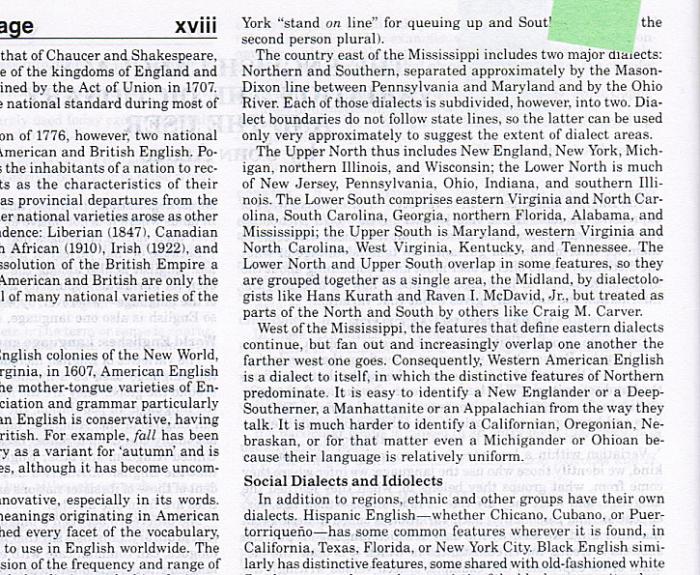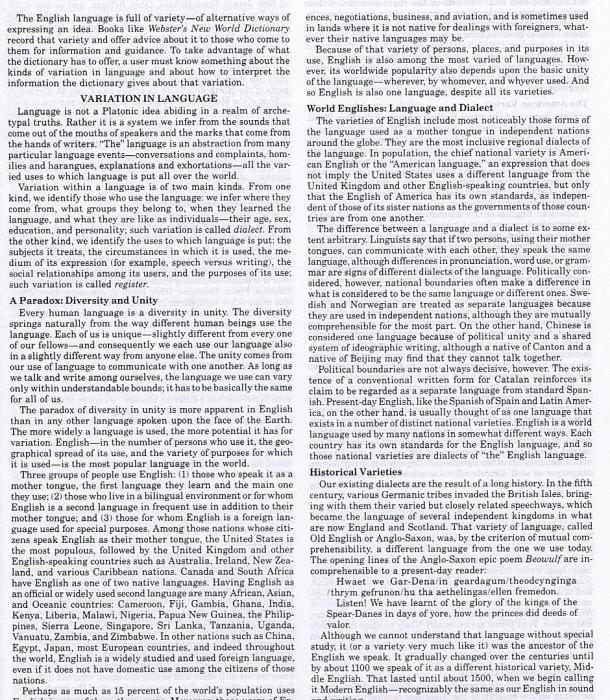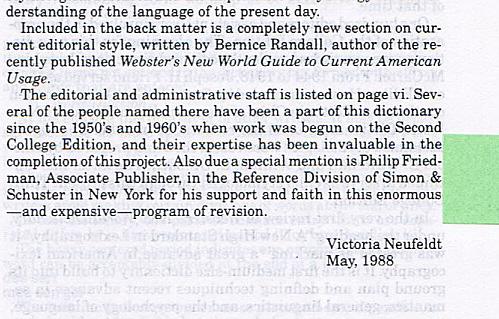
Der Bis-Strich im Englischen – wie wird der gehandhabt?
8th–9th November 2013
oder
8th – 9th November 2013
oder ganz anders?
Der — darf nicht verwendet werden ;-)
Aus (geisteswissenschaftlichen) Publikationen englischer und amerikanischer Verlage kenne ich nur den Halbgeviertstrich ganz ohne Leerraum; da handelt es sich allerdings nicht um Datumsangaben.
Ich kann mich an zwei Tagungsplakate erinnern, wo das Datum wie in Deinen Beispielen auftauchte – dort jeweils mit schmalem Leerraum davor und danach (bzw. im einen Fall, wo "th" hochgestellt war, nur mit zusätzlichem schmalem Leerraum danach, um die Abstände vor und nach dem Bis-Strich harmonisch zu gestalten). Also: kein ganzes Leerzeichen, aber ein bisschen Luft, damit der Bis-Strich nicht an den Zahlen klebt.
mathew butterick schreibt auf seiner seite „practicaltypography“:
The en dash has two uses.
1. It in­di­cates a range of values (1880–1912, pages 330–39, Exhibits A–E). If you open with from, pair it with to in­stead of an en dash (from 1880 to 1912, not from 1880–1912).
2. It de­notes a con­nec­tion or con­trast be­tween pairs of words (con­ser­v­a­tive–lib­er­al split, Arizona–Nevada reciprocity, Sarbanes–Oxley Act).
und weiter:
Em and en dash­es are typ­i­cal­ly set flush against the sur­round­ing text. Some fonts in­clude a lit­tle white space around the em dash; some don’t. If your em dash­es look like they’re be­ing crushed—par­tic­u­lar­ly if you’re set­ting type on screen—it’s fine to addword spaces be­fore and after.